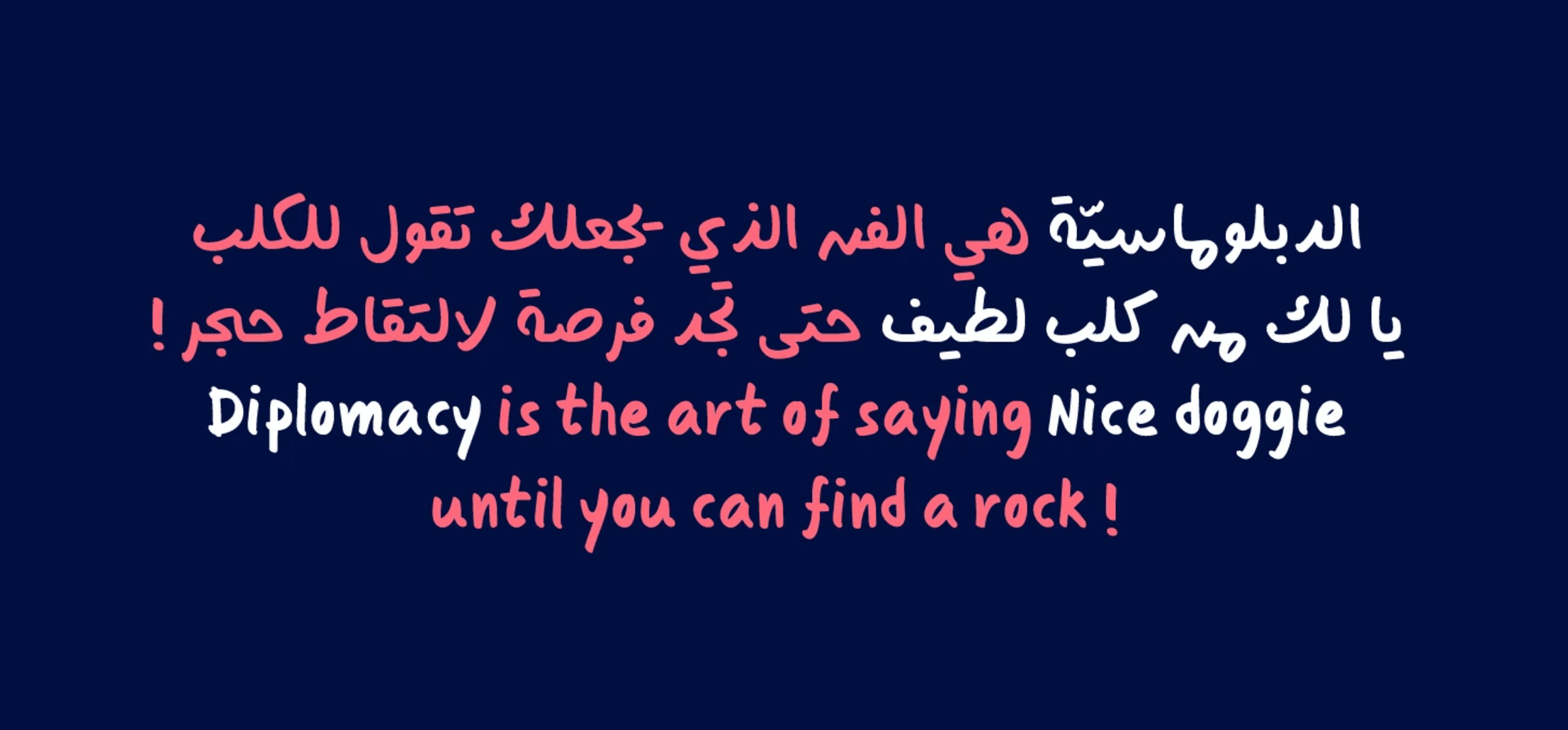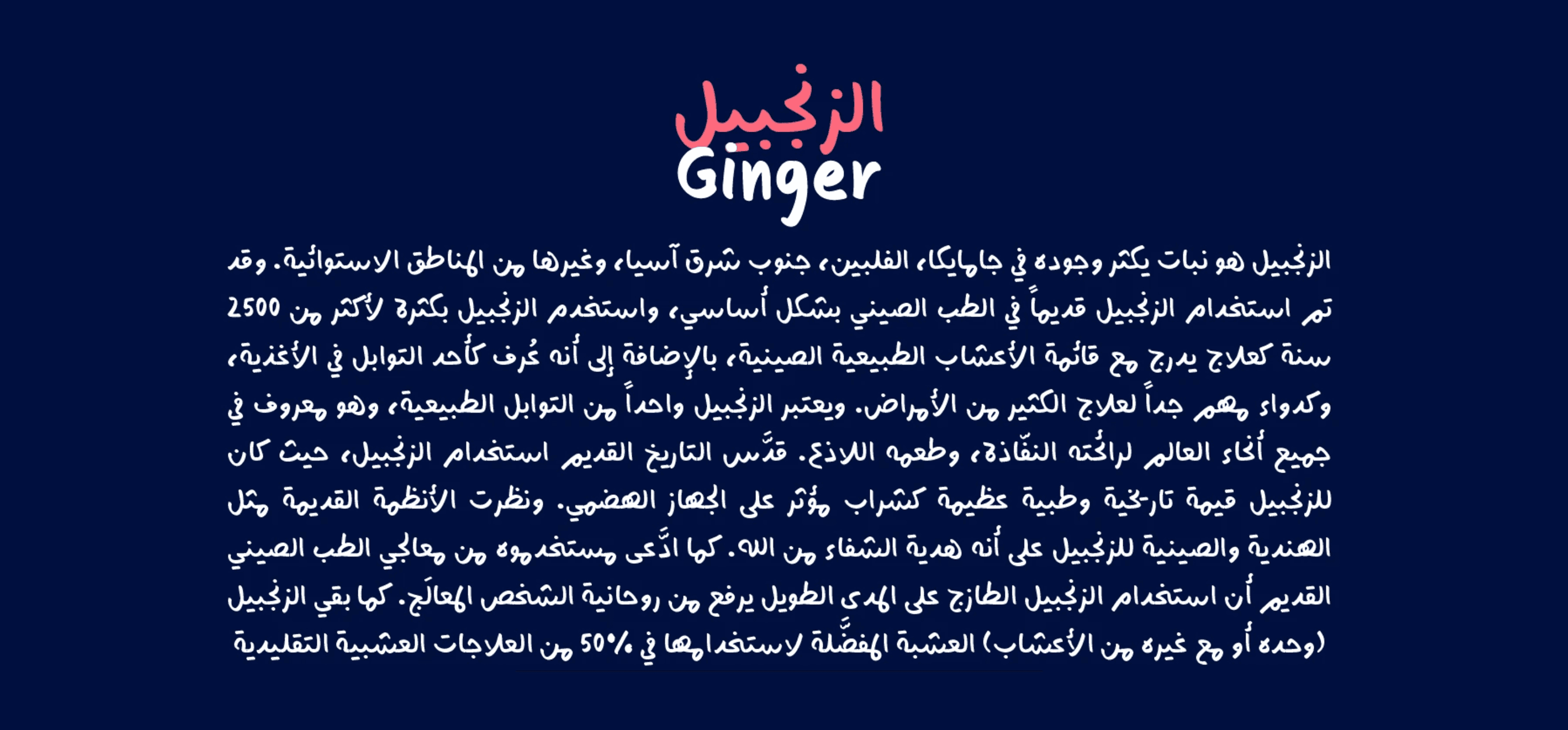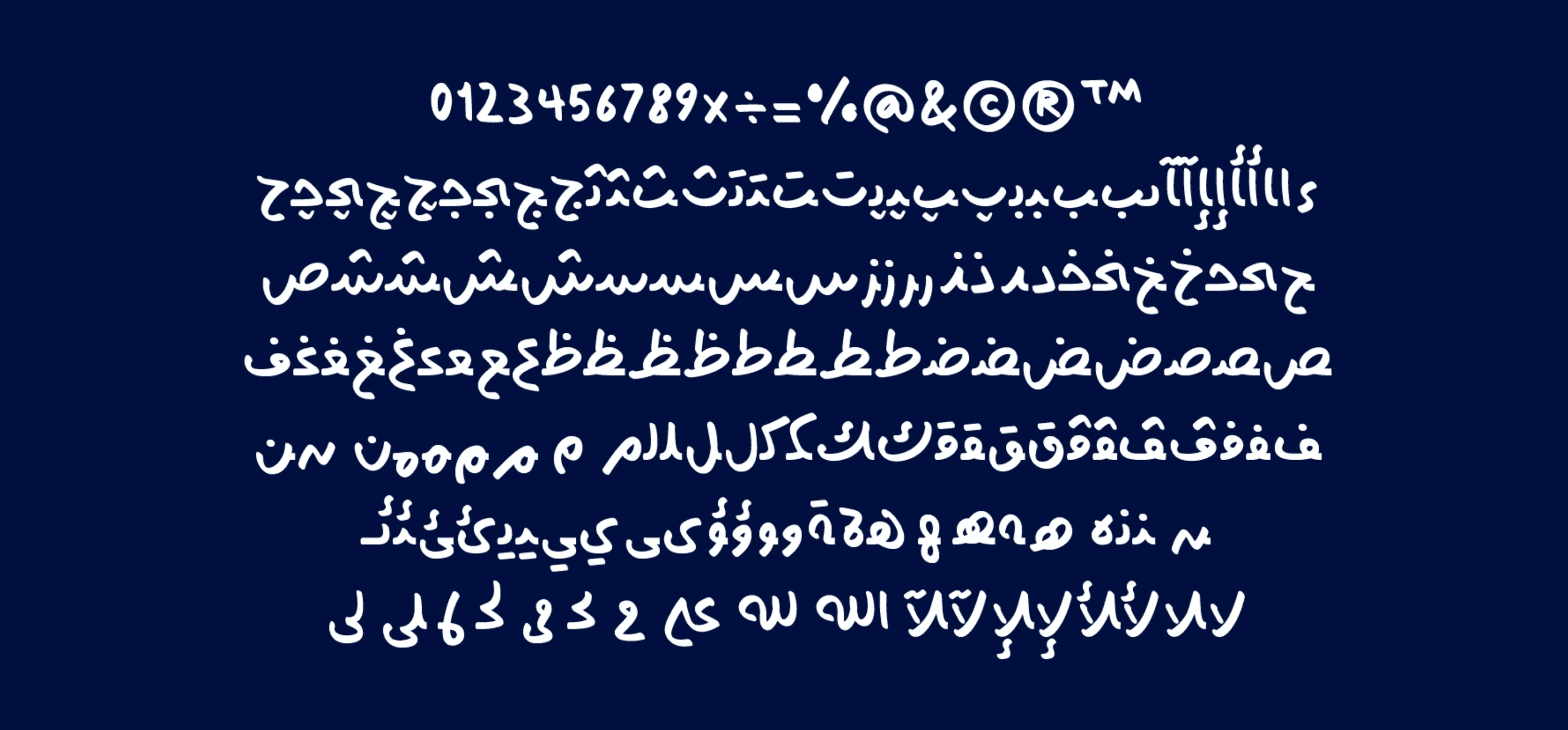
خط مُفرِح (Mufreh) هو خط يدوي عربي–لاتيني يتميز بأسلوبه السريع والعفوي، مستوحى من الكتابة الحرة والكاريكاتيرية. يجمع بين الطابع المرح والبسيط، مما يجعله مثاليًا للتصميمات غير الرسمية مثل الشعارات المرحة، العناوين الجذابة، وتصميمات الأطفال.
أهم خصائص الخط:
النوع: خط يدوي سريع وكاريكاتيري.
اللغات: يدعم العربية واللاتينية.
الطابع: ممتع، غير رسمي، حيوي.
المصمم: فهد الفريخ (Fahd Al Fraikh)، عام 2019.
خط مُفرِح (Mufreh) هو خط يدوي عربي–لاتيني يتميز بأسلوبه السريع والعفوي، مستوحى من الكتابة الحرة والكاريكاتيرية. يجمع بين الطابع المرح والبسيط، مما يجعله مثاليًا للتصميمات غير الرسمية مثل الشعارات المرحة، العناوين الجذابة، وتصميمات الأطفال.
أهم خصائص الخط:
النوع: خط يدوي سريع وكاريكاتيري.
اللغات: يدعم العربية واللاتينية.
الطابع: ممتع، غير رسمي، حيوي.
المصمم: فهد الفريخ (Fahd Al Fraikh)، عام 2019.
خط مُفرِح (Mufreh) هو خط يدوي عربي–لاتيني يتميز بأسلوبه السريع والعفوي، مستوحى من الكتابة الحرة والكاريكاتيرية. يجمع بين الطابع المرح والبسيط، مما يجعله مثاليًا للتصميمات غير الرسمية مثل الشعارات المرحة، العناوين الجذابة، وتصميمات الأطفال.
أهم خصائص الخط:
النوع: خط يدوي سريع وكاريكاتيري.
اللغات: يدعم العربية واللاتينية.
الطابع: ممتع، غير رسمي، حيوي.
المصمم: فهد الفريخ (Fahd Al Fraikh)، عام 2019.